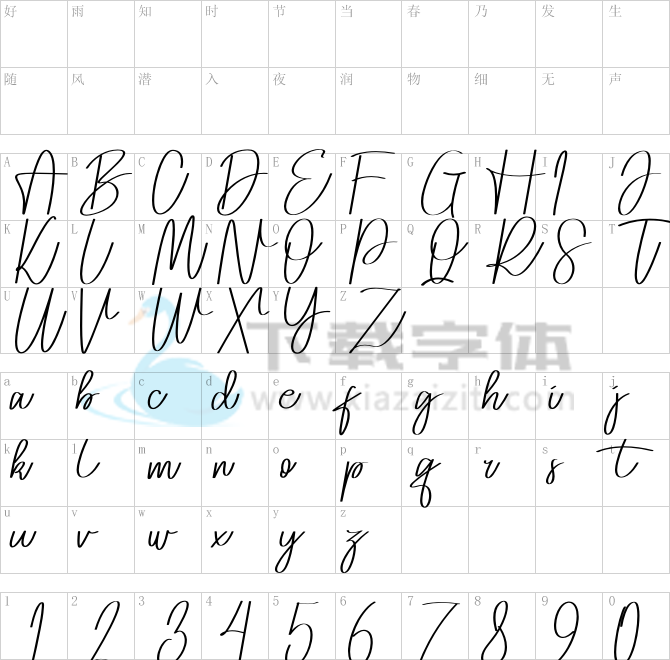
Afontros.ttf字体下载
Afontros.ttf字体下载,这款字体结构工整、笔画清晰,兼顾美观与易读性,适用于标题、正文、海报、包装、LOGO 等多种场景。字形优雅稳定,风格百搭耐看,适配日常排版与创意设计,让文字呈现更舒适、更具质感。Afontros.ttf字体下载一笔一画,皆是细节,以均衡的比例、流畅的线条打造舒适视觉体验,字形端正大气,风格简约现代。无论是商业设计、品牌宣传还是日常排版,都能轻松驾驭,让文字更有格调与力量。Afontros.ttf字体下载字体下载。